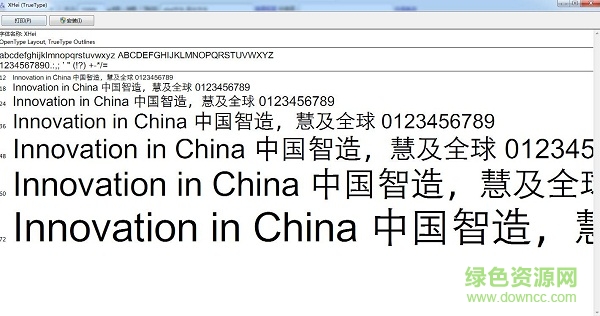
xhei字體第6版
xhei 6th字體是一款ttf格式的仿蘋(píng)果黑體字體,簡(jiǎn)潔無(wú)裝飾,美觀又實(shí)用,綠色資源網(wǎng)還有標(biāo)準(zhǔn)黑體、思源黑體、方正黑體、漢儀黑體、微軟黑體等海量高品質(zhì)的黑體字體供大家免費(fèi)下載!歡迎體驗(yàn)!
黑體字體的優(yōu)勢(shì)
1.黑體字的橫豎筆畫(huà)的粗細(xì)要相對(duì)一直,“人工設(shè)計(jì)”的效果也更強(qiáng),常被用于作為“力量較強(qiáng)的效果”和“時(shí)尚的效果”的處理;
2.標(biāo)題如果選用黑體來(lái)處理,會(huì)比宋體更容易給人帶來(lái)較為強(qiáng)烈的印象,因此黑體字的直觀效果相對(duì)于宋體等手寫(xiě)體來(lái)說(shuō)要更強(qiáng)一些。